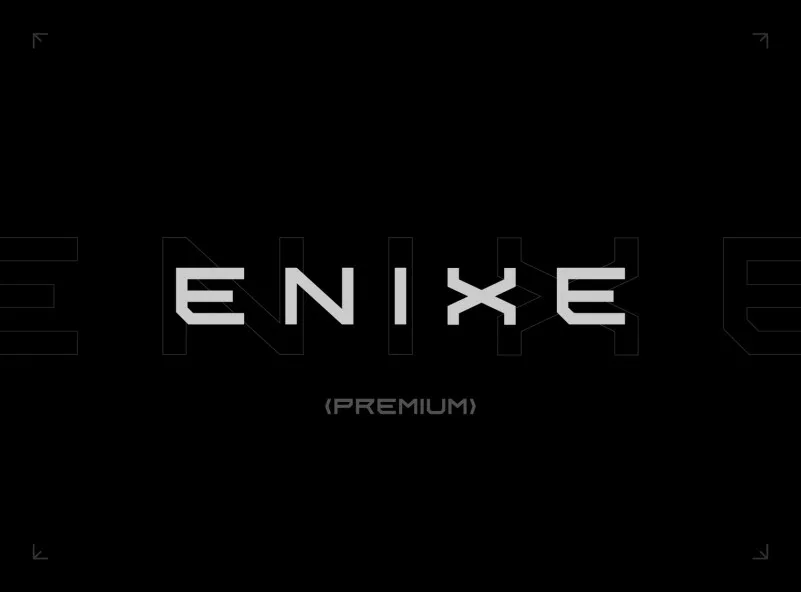
A Enixe Font é uma tipografia futurista com uma aparência tecnológica avançada. Ela inclui letras maiúsculas, números e pontuação, embora alguns caracteres possuam versões alternativas que podem ser ativadas através da tecla de Caps Lock. Perfeita para escritas em designs web, cards empresariais ou qualquer outra coisa que necessite de uma toque único. Esta fonte apresenta um visual moderno e inovador, ideal para quem busca destaque em seu trabalho gráfico. Seja você criando cartões de visita com um toque de personalidade, trabalhando em projetos web digitais ou apenas querendo dar um novo ímpeto à sua arte gráfica, a Enixe Font está aqui para ajudá-lo a chegar ao próximo nível.